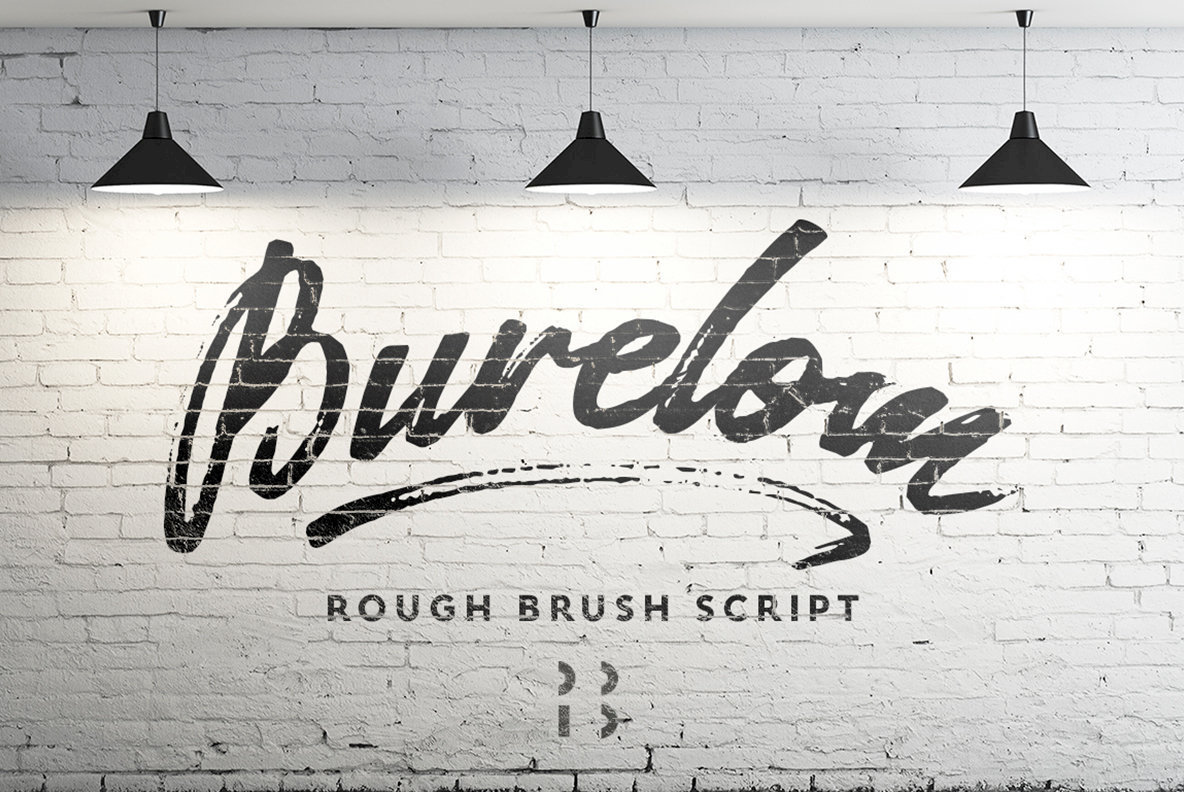
16 лучших бесплатных кириллических шрифтов 2016 года — Оди
В подборку вошли самые качественные кириллические шрифты, выпущенные в прошлом году.
Акцидентный шрифт, основанный на каллиграфии Дарьи Квон. Он был начат на онлайн-курсе «Свой шрифт» в TypeTypeSchool в августе 2016 года. Шрифт содержит базовый набор кириллических знаков, а также расширенную кассу знаков для латиницы.
Акцидентный гротеск с узкими пропорциями и низким контрастом, созданный на основе допетровской кириллицы и стилизованный под модерн. 2 начертания: обычное и наклонное. Мультиязычный: латиница, кириллица, расширенная латиница, расширенная кириллица.
Подойдёт для заголовков и небольших объёмов текста, логотипов и иллюстраций, плакатов и упаковки. Автор Миша Панфилов.
Гарнитура из дополняющих друг друга нео-гротесков и рукописных шрифтов. Бесплатно одно начертание. Дизайнер Ани Петрова, Фонтфабрик.
Акцидентный шрифт, стилизованный под антикву нового стиля.
Немного зауженный гротеск с достаточно качественной кириллицей. Все 8 начертаний гарнитуры бесплатны для личного и коммерческого применения.
Гуманистический гротеск с кириллицей. В гарнитуре 8 обычных начертаний и 8 курсивных. Бесплатно раздают 2 начертания, Медиум и Медиум Италик. Остальные продаются по 25$ за штуку или за 320$ за все. Дизайнер Глен Жан из Уфы.
Слово авторам: «Нежный и добрый цветочный шрифт, который производит впечатление своей естественной красотой. Шрифт Магнолия — это определенно девушка, можно даже сказать шрифтесса, которая расцвела и готова подарить свою красоту окружающему миру».
Автор шрифта Таня Черкиз, арт-директор Иван Гладких, инженер шрифта Денис Сериков.
Бесплатный декоративный шрифт.
Частично бесплатный узкий гротеск с кириллицей.
Бесплатный гротеск с кириллицей. Дизайнер шрифта Сергей Рядовой, в качестве арт-директора выступил известный шрифтовой дизайнер Иван Гладких (TypeType). В шрифте качественная кириллица, а также поддержка многих других языков.
Антиква с кириллицей в 6 начертаниях (одно бесплатно, остальные по 1400₽). Автор Миша Панфилов.
Новый бесплатный шрифт с кириллицей. Шрифт создан на основе популярных в 60-е буквенных форм (см. надписи на ст. метро «Таганская» и «Коломенская» московского метрополитена), но в своём развитии отошёл достаточно далеко от прототипа. Oks может применяться в кеглях от 36 и выше (можно и ниже, но в таком случае потребуется принудительная разрядка). Содержит только прописные знаки. Расширен небольшим набором лигатур, в том числе кириллических. Свободен для личного и коммерческого применения.
Серия из трех рукописных шрифтов.
Рукописный шрифт с «партизанским» характером. Автор Карлос Зубия из Мексики.
30 высококачественных бесплатных шрифтов для дизайна
Шрифты являются полезным ресурсом для любого дизайнера. С их помощью вы сможете придать определенный стиль и выразить смысл своей работы. В шрифтах, также как и в дизайне, есть множество направлений. Они могут быть простыми и чистыми, с потеками краски в стиле гранж, урбанистическими, восточными, фигурными, 3D и так далее.
Многослойный шрифт Morning Glory
Крупный шрифт Tondu Beta
Шрифт в кантри стиле Legion Slab
Шрифт в восточном стиле Excellence
Ровный шрифт Alt Ayame
Креативный шрифт Pacifica